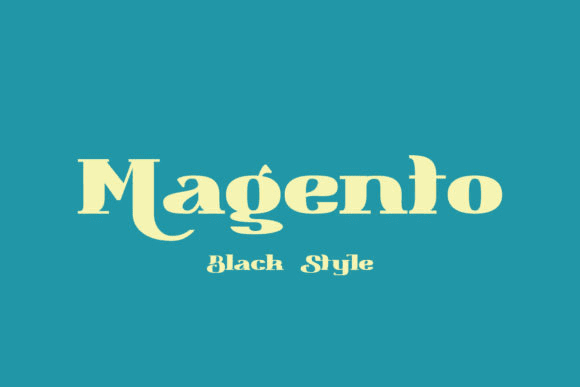
Название: Magento Font
Magento - стильный и смелый шрифт с наклонной засечкой.
Отличаясь выразительными и внушительными символами, Magento станет прекрасным дополнением к вашей библиотеке шрифтов.
Добавляйте его уверенно, и вам понравится его влияние на ваши проекты.